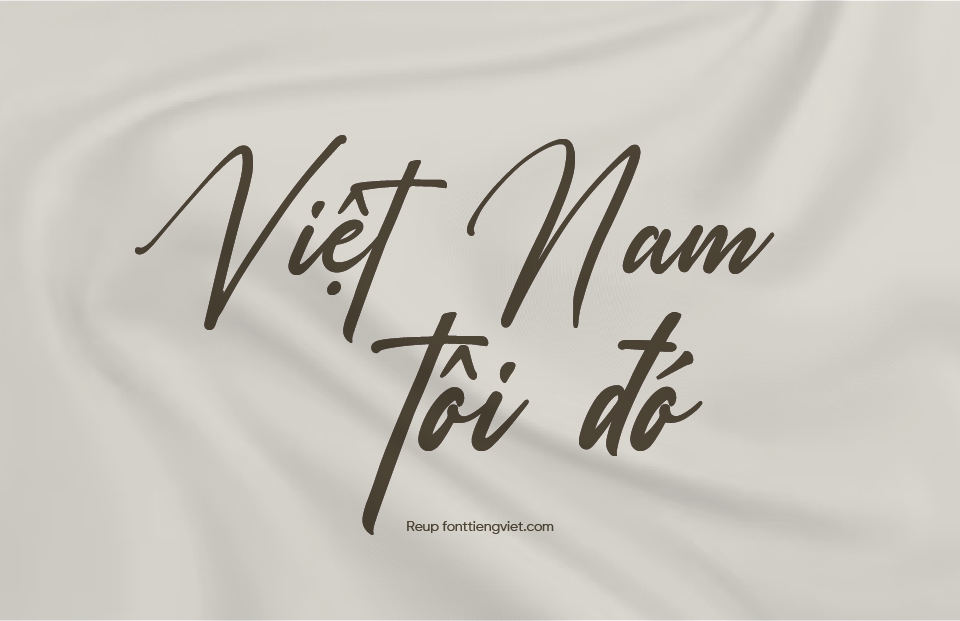
Font Việt hóa SVN Rosellinda Alyamore
Font Việt hóa SVN Rosellinda Alyamore – Lựa chọn hoàn hảo cho thiết kế bay bổng
Giới thiệu về Font Việt hóa SVN Rosellinda Alyamore
Trong thế giới sáng tạo, việc tìm kiếm một Font Miễn Phí chất lượng luôn là ưu tiên hàng đầu của các nhà thiết kế. Font Việt hóa SVN Rosellinda Alyamore nổi lên như một biểu tượng của sự thanh lịch và tinh tế. Đây là một phông chữ thuộc phong cách Script với những đường nét uốn lượn mềm mại, mang lại cảm giác thủ công tự nhiên cho mọi tác phẩm nghệ thuật. Việc sử dụng bộ chữ này giúp truyền tải thông điệp một cách nhẹ nhàng nhưng không kém phần ấn tượng, đặc biệt phù hợp với thị hiếu thẩm mỹ tại Việt Nam.
Đặc điểm nổi bật của bộ Font Việt hóa SVN Rosellinda Alyamore
Thiết kế thanh thoát và đa dụng
Font Việt hóa SVN Rosellinda Alyamore sở hữu cấu trúc các ký tự nối liền nhau rất mượt mà. Điểm mạnh của bộ font này chính là các ký tự thay thế (alternates) và các đường gạch nối (ligatures) phong phú, giúp người dùng dễ dàng tùy biến theo ý thích. Nhờ quá trình Việt hóa kỹ lưỡng, các dấu tiếng Việt được đặt vị trí chuẩn xác, không gây tình trạng lỗi font hay mất cân đối khi soạn thảo văn bản dài.
Ứng dụng trong giáo dục và đời sống
Đối với học sinh và giáo viên, phông chữ này cực kỳ hữu ích trong việc thiết kế thiệp chúc mừng, bìa báo tường hay các bài thuyết trình nghệ thuật. Sự gần gũi và dễ đọc của nó giúp các em học sinh tiếp cận với tư duy thẩm mỹ hiện đại một cách tự nhiên nhất.
Kết luận về trải nghiệm người dùng